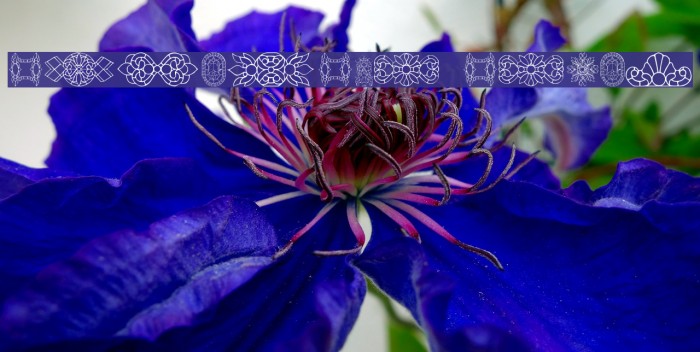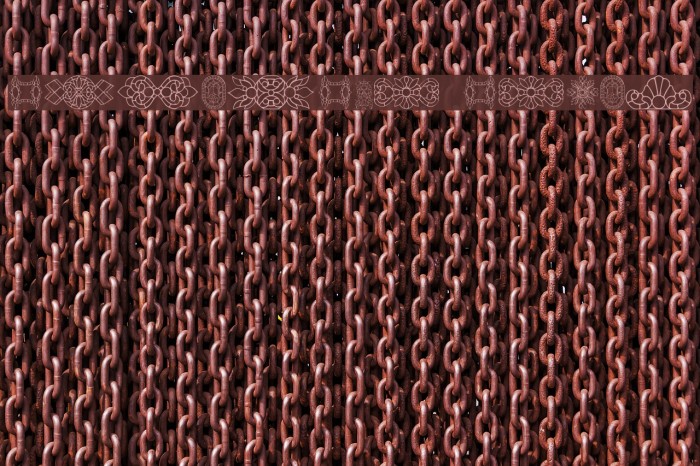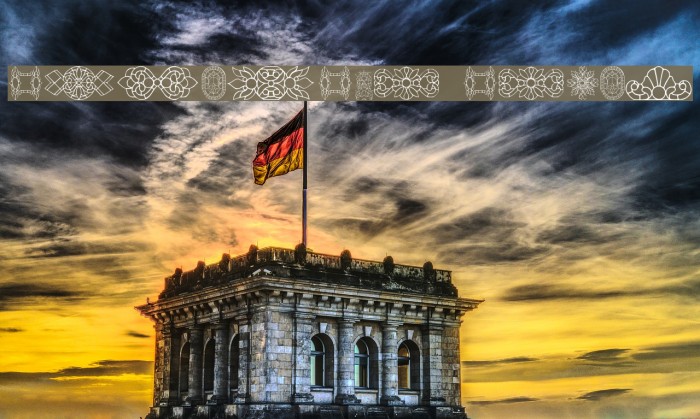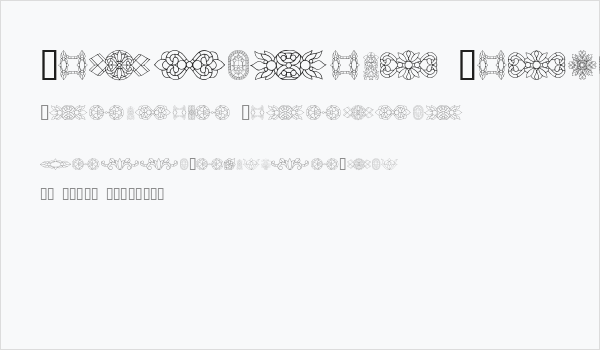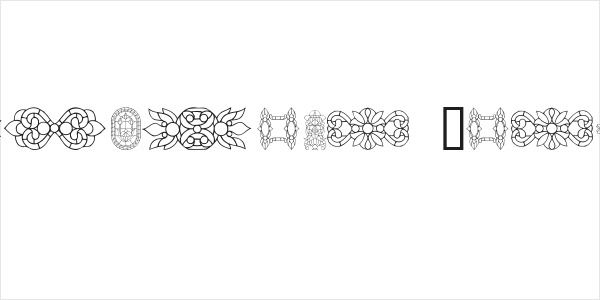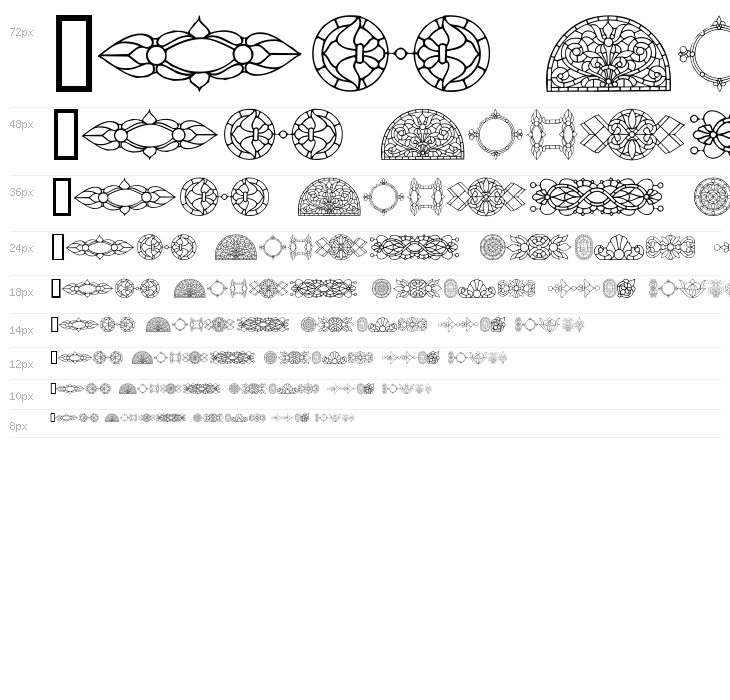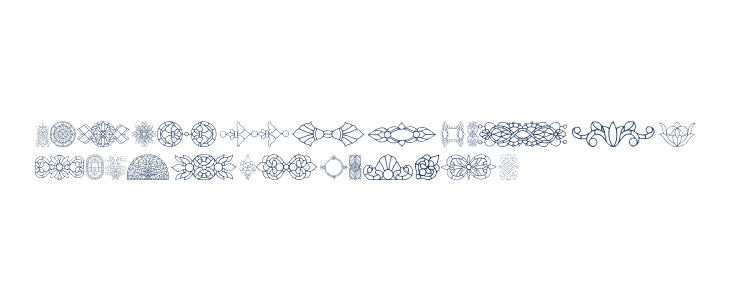
Victorian Window Font
| Caso de uso | Decorative elements, Architectural designs |
| Projetos propostos | Ideal for use in vintage-themed graphic designs, historical recreations, or as decorative elements in architectural renderings. |